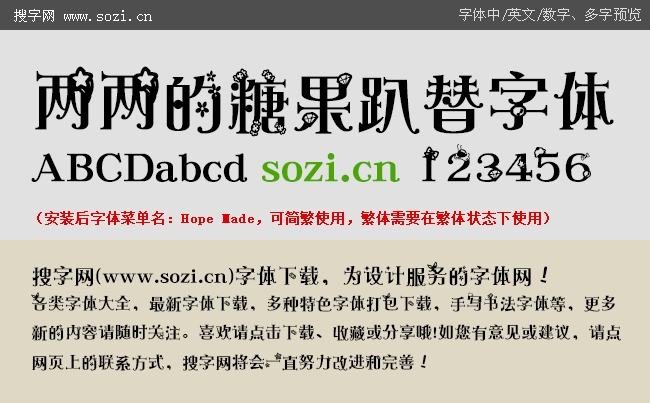
兩兩的糖果趴替字體
搜字網(wǎng)給大家提供一款兩兩的糖果趴替字體手機(jī)中文字體下載。這款手機(jī)字體是在華康飾藝體筆畫間插入了可愛的卡通圖案。華康飾藝體是一款帶有西方古典美的字體,橫細(xì)豎粗,起筆落筆處加有西方特色的櫬線裝飾,跟西方的花體字很類似。加入了卡通圖案后更增添了趣味性,特別適合喜歡手機(jī)字體個(gè)性一些的朋友在手機(jī)上安裝使用。